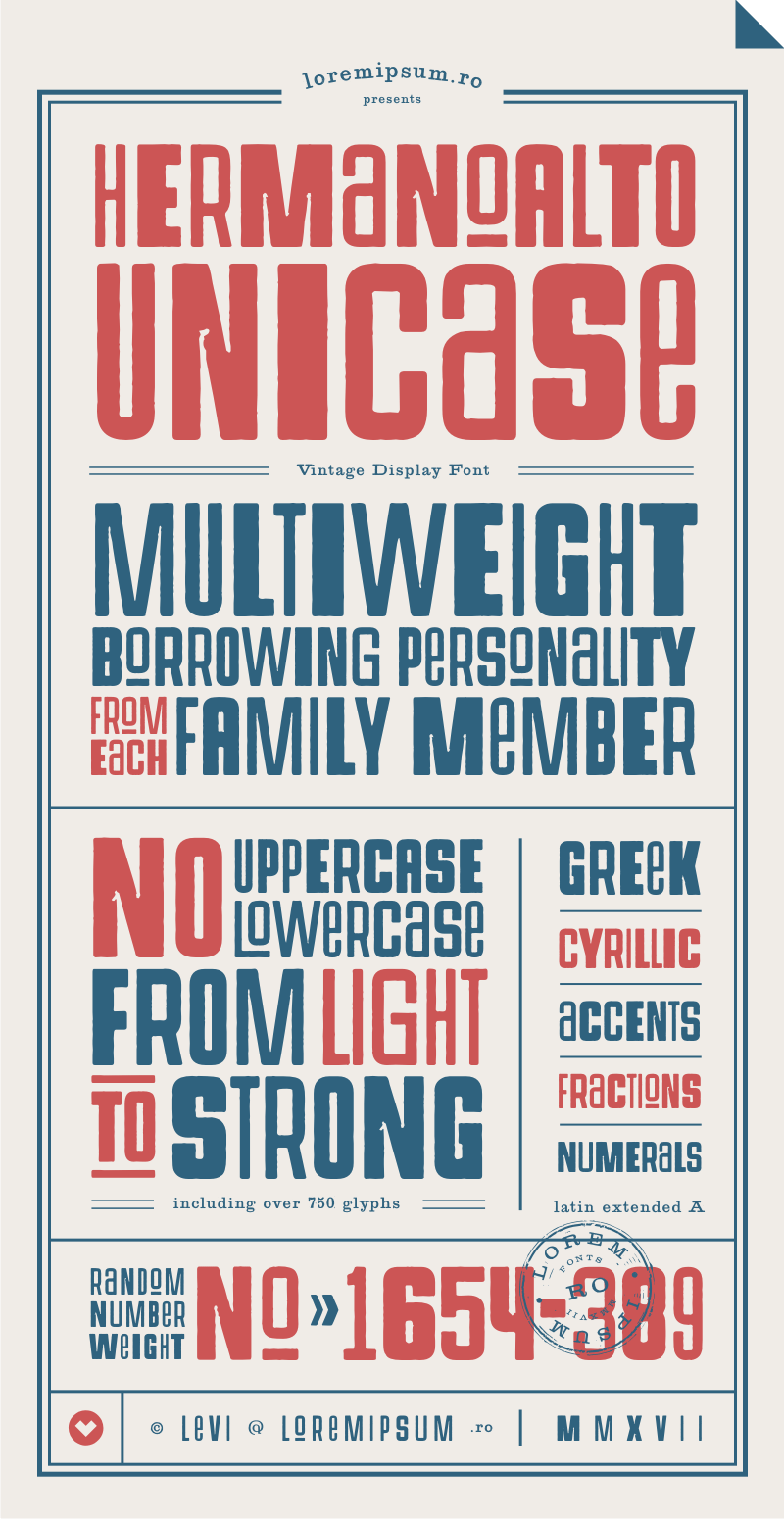
Hermanoalto Unicase Font
A HermanoAlto Unicase é uma fonte sans-serif que incorpora linhas de todos os tipos na família HermanoAlto até então criada. Esta nova fonte foi ajustada para ter alturas iguais, mas com variações nas larguras e estilos (incluindo as versões Líte, Regular e Bold). Além disso, foram adicionados novos caracteres Wide, Extended e Condensed. O efeito de erosão suave foi aplicado à fonte para aproximar-a do estilo dos desenhos gráficos feitos até o meio do século XX. Esta é uma fonte ideal para criar design gráfico moderno com um toque nostálgico, perfeita para aplicativos que exigem versatilidade e sofisticação. Se você busca uma fonte sans-serif que mantenha a elegância das fases posteriores do século passado, então HermanoAlto Unicase é seu tipo certo. Uma ótima opção para designers gráficos em busca de um design inovador com uma atmosfera nostálgica e versátil.